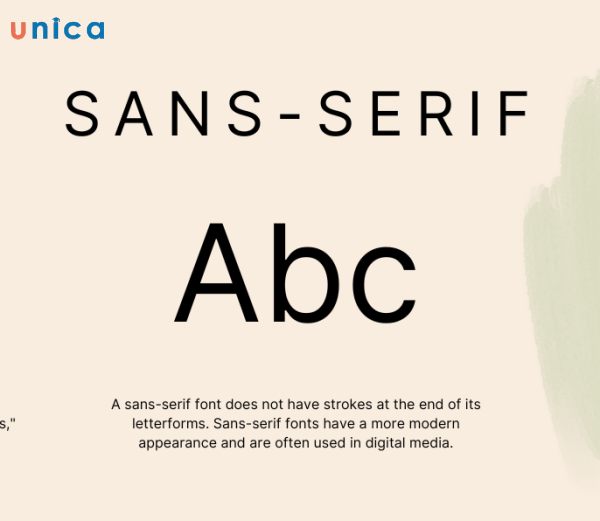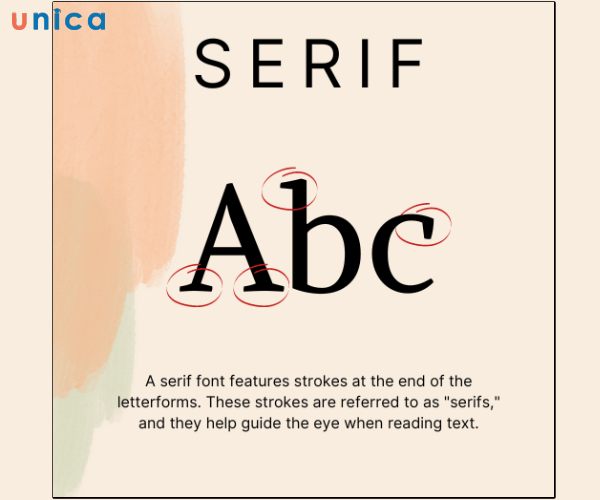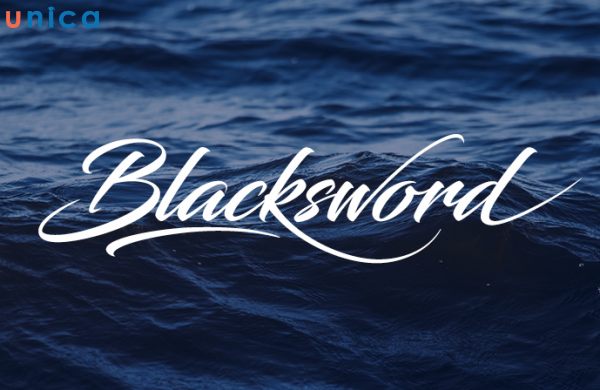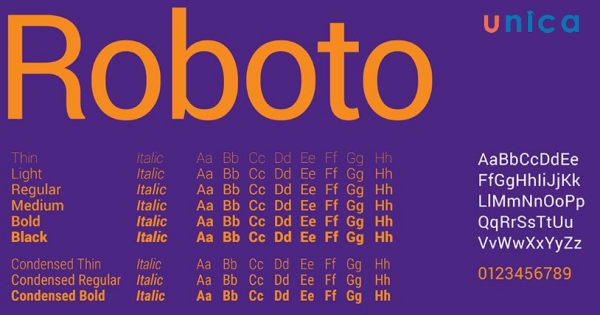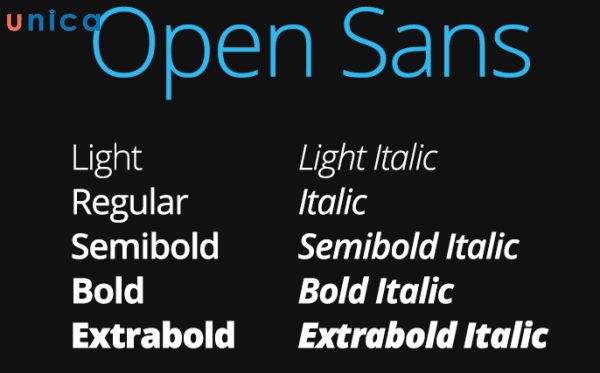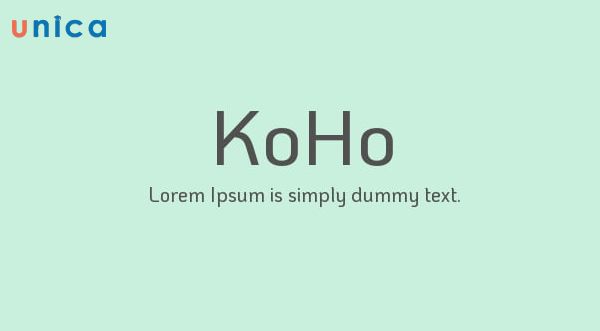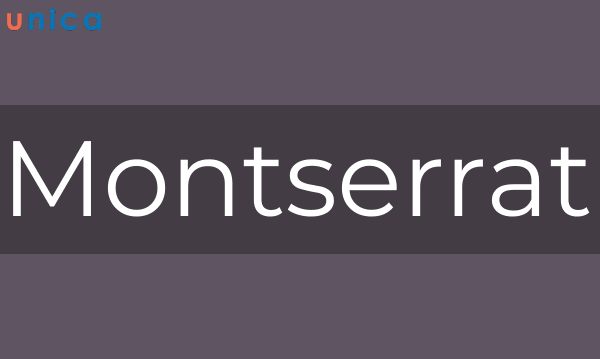
Font chữ là một yếu tố quan trọng trong thiết kế slide PowerPoint, giúp bạn thể hiện nội dung, phong cách và tâm trạng của bài trình chiếu của mình. Font chữ cũng ảnh hưởng đến sự chú ý, nhận thức và trí nhớ của khán giả đối với bài trình chiếu của bạn. Bạn có biết cách thêm Font chữ vào PowerPoint không? Bạn có biết những kiểu Font chữ nào giúp slide trông chuyên nghiệp hơn không? Bạn có biết cách tùy chỉnh Font chữ theo ý muốn của mình không? Nếu bạn chưa biết, hãy đọc bài viết này để tìm hiểu cách tải font chữ về powerpoint và những tùy chỉnh Font chữ đơn giản.
Một số kiểu font chữ giúp slide trông chuyên nghiệp hơn
Trước khi học cách tải font chữ về powerpoint, bạn cần biết một số kiểu Font chữ giúp slide trông chuyên nghiệp hơn. Có nhiều kiểu Font chữ khác nhau nhưng không phải kiểu Font chữ nào cũng phù hợp với mọi bài trình chiếu. Bạn cần chọn kiểu Font chữ phù hợp với nội dung, mục tiêu và đối tượng của bài trình chiếu của mình. Dưới đây là một số kiểu Font chữ phổ biến và thường được sử dụng trong PowerPoint:
1. Sans Serif
Sans Serif là kiểu Font chữ không có những đường nhỏ ở cuối các nét chữ, giúp chữ trông đơn giản và hiện đại. Sans Serif thường được sử dụng cho các bài trình chiếu mang tính chất chính thức, chuyên nghiệp, hoặc khoa học. Một số ví dụ về Font chữ Sans Serif là Arial, Calibri, Helvetica, Verdana,...
Sans Serif là kiểu Font chữ không có những đường nhỏ ở cuối các nét chữ
2. Serif
Serif là kiểu Font chữ có những đường nhỏ ở cuối các nét chữ, giúp chữ trông cổ điển, trang nhã hơn. Serif thường được sử dụng cho các bài trình chiếu mang tính chất văn hóa, nghệ thuật hoặc lịch sử. Một số ví dụ về Font chữ Serif là Times New Roman, Georgia, Garamond, Cambria,...
Serif là kiểu Font chữ có những đường nhỏ ở cuối các nét chữ, giúp chữ trông cổ điển, trang nhã hơn
3. Script
Script là kiểu Font chữ bắt chước chữ viết tay thông dụng mà khi bạn thực hiện cách tải font chữ về powerpoint sẽ thường xuyên bắt gặp. Script thường được sử dụng cho các bài trình chiếu mang tính chất cá nhân, thư giãn hoặc giải trí. Một số ví dụ về Font chữ Script là Brush Script, Lucida Handwriting, Segoe Script, Edwardian Script,...
Script là kiểu Font chữ bắt chước chữ viết tay, giúp chữ trông thân thiện, sáng tạo và cảm xúc
4. Font Roboto
Font Roboto là một kiểu Font chữ được thiết kế bởi Google, giúp chữ trông hiện đại, minh bạch và thân thiện. Font Roboto thường được sử dụng cho các bài trình chiếu liên quan đến công nghệ, thiết kế hoặc truyền thông. Font Roboto có nhiều biến thể như Roboto Thin, Roboto Light, Roboto Regular, Roboto Medium, Roboto Bold,...
Font Roboto là một kiểu Font chữ được thiết kế bởi Google, giúp chữ trông hiện đại, minh bạch và thân thiện
5. Font Open Sans
Font Open Sans là một kiểu Font chữ được thiết kế bởi Google. Kiểu chữ này đơn giản và dễ đọc nên khi thực hiện cách tải font chữ về powerpoint chắc hẳn bạn sẽ thường dùng kiểu này. Font Open Sans thường được sử dụng cho các bài trình chiếu mang tính chất chung. Font Open Sans cũng có nhiều biến thể như Open Sans Light, Open Sans Regular, Open Sans Semibold, Open Sans Bold,...
Font Open Sans là một kiểu Font chữ được thiết kế bởi Google
6. Font Koho
Font Koho là một kiểu Font chữ được thiết kế bởi người Việt Nam, giúp chữ trông độc đáo, nghệ thuật và phong cách. Font Koho thường được sử dụng cho các bài trình chiếu mang tính chất sáng tạo, nổi bật hoặc thể hiện cá tính. Font Koho có nhiều biến thể như Koho Thin, Koho Light, Koho Regular, Koho Medium, Koho Bold,...
Font Koho là một kiểu Font chữ được thiết kế bởi người Việt Nam, giúp chữ trông độc đáo
7. Font Montserrat
Font Montserrat là một kiểu Font chữ được thiết kế bởi người Argentina, giúp chữ trông sang trọng, tinh tế và thanh lịch. Font Montserrat thường được sử dụng cho các bài trình chiếu mang tính chất cao cấp, thời trang hoặc quảng cáo. Font Montserrat cũng có nhiều biến thể như Montserrat Thin, Montserrat Light, Montserrat Regular, Montserrat Semibold, Montserrat Bold,...
Font Montserrat là một kiểu Font chữ được thiết kế bởi người Argentina, giúp chữ trông sang trọng, tinh tế và thanh lịch
8. Font Fira Sans
Font Fira Sans là một kiểu Font chữ được thiết kế bởi Mozilla, giúp chữ trông hiện đại, rõ ràng và linh hoạt. Font Fira Sans thường được sử dụng cho các bài trình chiếu liên quan đến mạng, trình duyệt hoặc mã nguồn. Font Fira Sans cũng có nhiều biến thể như Fira Sans Thin, Fira Sans Light, Fira Sans Regular, Fira Sans Medium, Fira Sans Bold,...